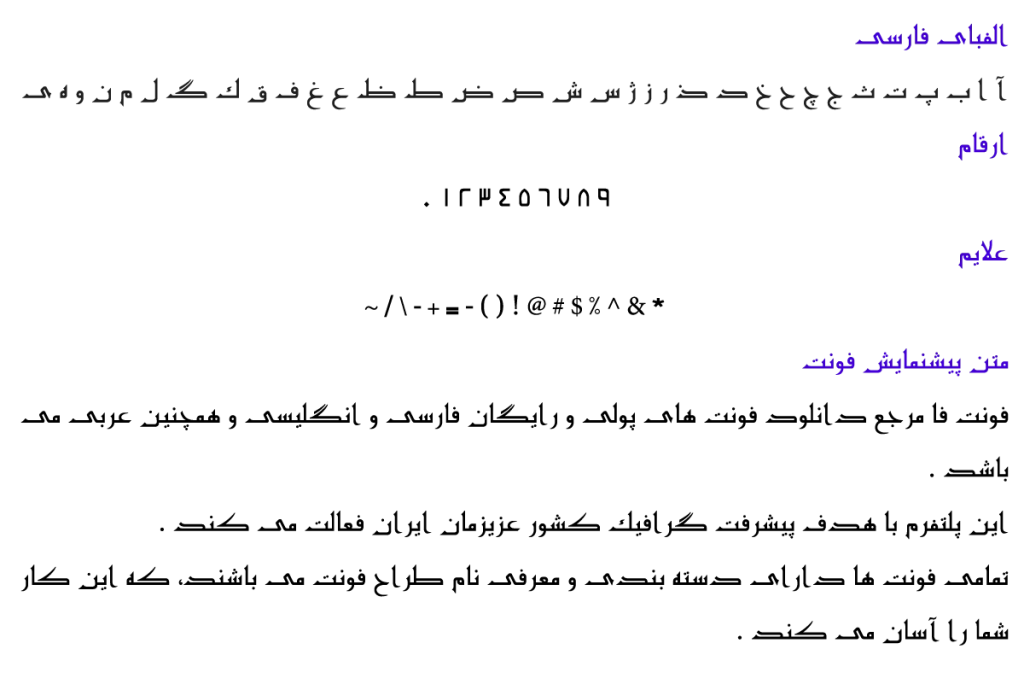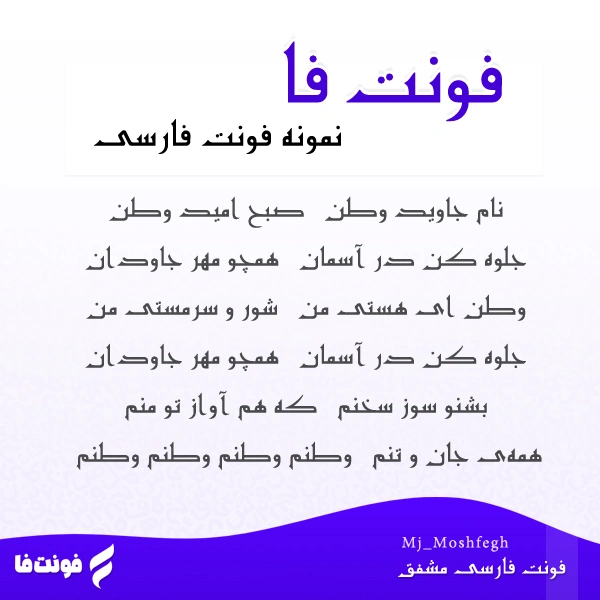
فونت فارسی مشفق – Mj Moshfegh
طراح فونت: مجتبی کیا نوع فونت: فونت هندسی
پیشنمایش فونت مشفق
توضیحات و معرفی فونت مشفق
فونت فارسی مشفق ( Mj Moshfegh ) از مجموعه فونت های سری Mj می باشد، و نیز نوع فونت هندسی می باشد.
فونت خوشگل مربوط توسط مجتبی کیا در سال 1390 طراحی و ساخته شده است.
و نیز فونت Mj Moshfegh در 2 وزن پر رنگ و معمولی است.
شعر میهنی زیر با این تایپ فیس طراحی شده و نمایانگر زیبایی آن است.